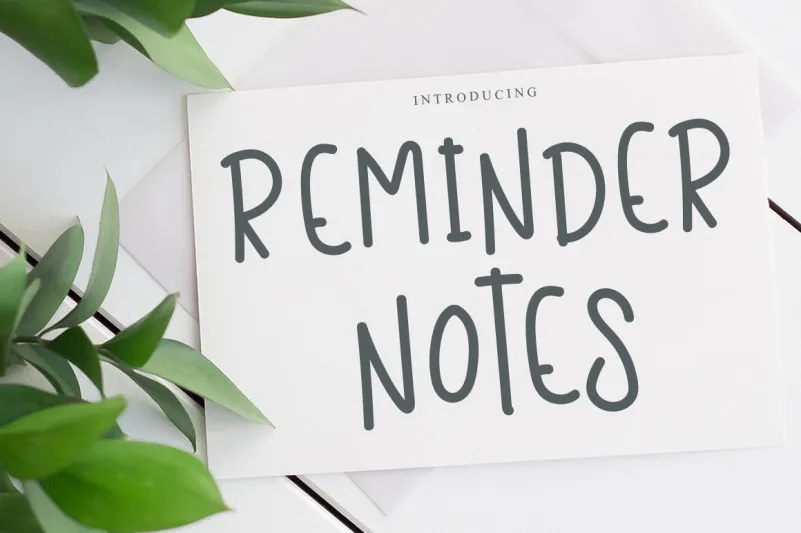
Reminder Notes Font – Fonte Grátis
Reminder Notes Font
Esta fonte ‘Reminder Notes Font’ é projetada para dar um toque amigável e alegre às suas criações digitais. Inspirada no estilo da escrita infantil, tem uma aparência limpa e moderna, ideal para aqueles que buscam uma pausa casual em seu trabalho de design. Seu caráter levemente irônico e divertido garante um toque único e alegre sem deixar de ser profissional. Adicionar esta font ao seu próximo projeto significa transformá-lo com leveza e criatividade, oferecendo-lhe uma opção para criar designs que não apenas destaquem-se, mas também trazam um sorriso aos olhos do seu público. Não importa se você está trabalhando em um design de logotipo ou simplesmente anotando suas notas diárias, o resultado será animado e único, feito especialmente para o seu estilo criativo.